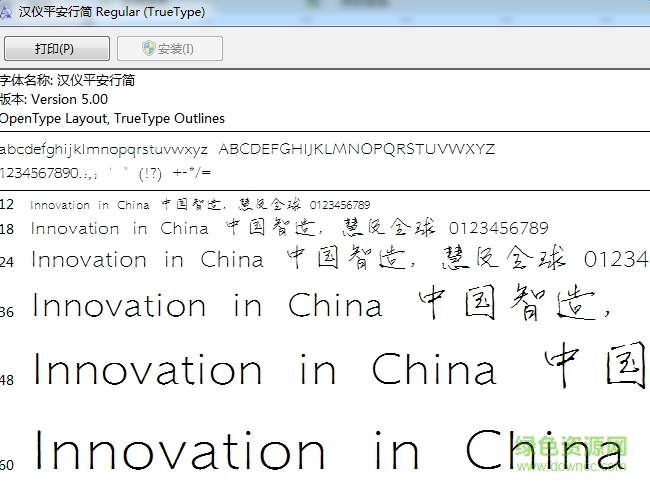
漢儀平安行簡字體是一款漢儀字體庫中的個(gè)性字體,該字體可以廣泛應(yīng)用于廣告設(shè)計(jì)、宣傳海報(bào)、ppt、影視制作以及任何使用文字的領(lǐng)域,有需要的朋友可以免費(fèi)下載收藏。
漢儀平安行簡字體是一款極具個(gè)性的漢儀字體,該字體擁有非常飄逸的字型,有喜歡的朋友就來綠色資源網(wǎng)下載使用吧!